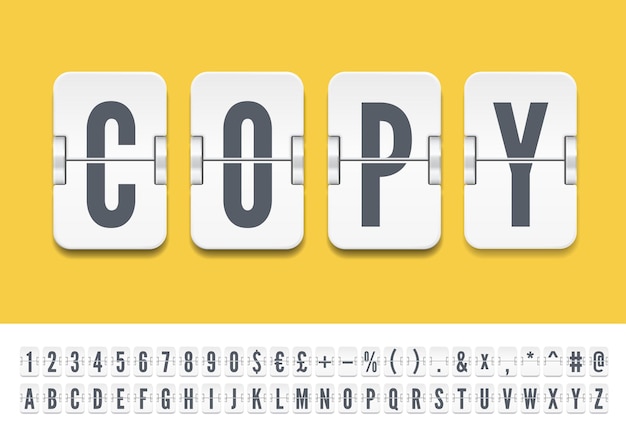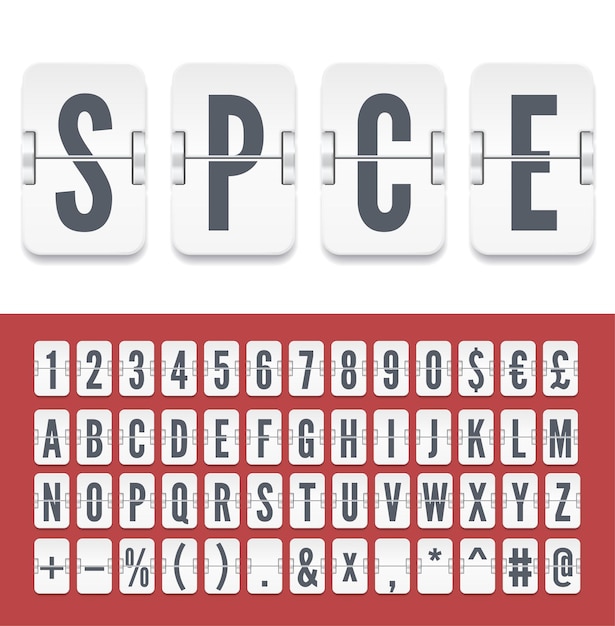
Флип белый таймер обратного отсчета алфавит изолирован на синем фоне Винтаж флип часы счетчик времени вектор шаблон для призыва к действию реклама Векторная иллюстрация Табло ретро шрифт